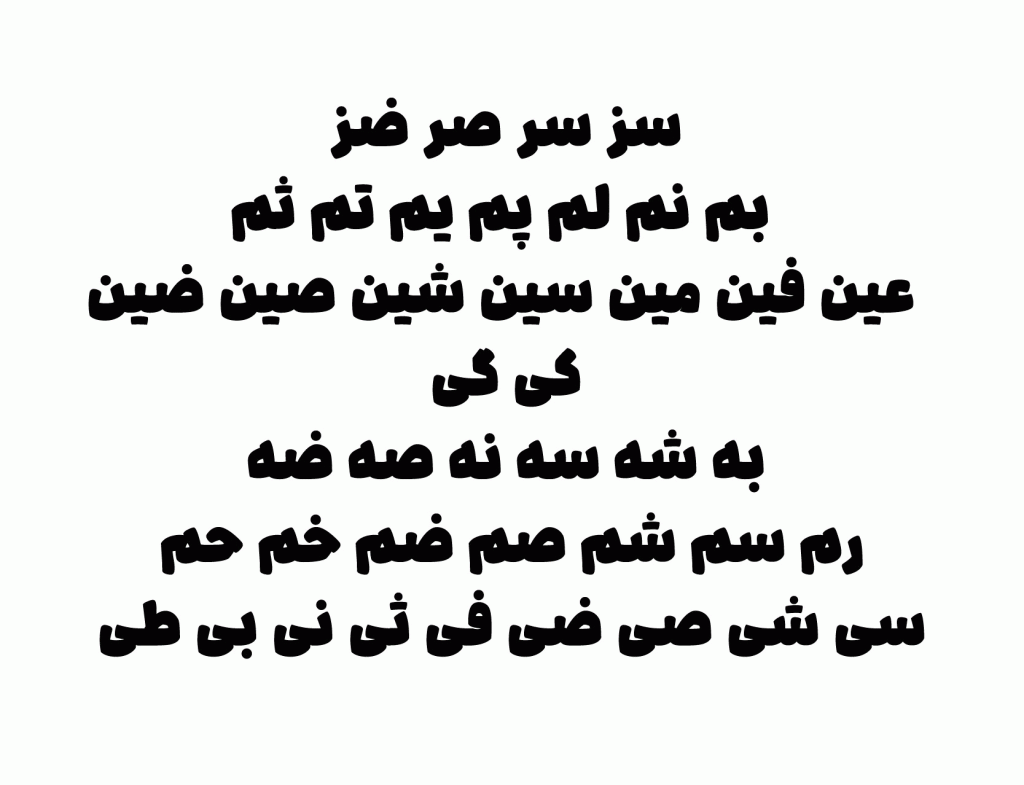
فونت چکاد – قلمی برای جذب نگاه مخاطبان
فونت چکاد تایپ فیسی که ایده و مدل طراحی آن از به قرن ها پیش باز می گردد . ای قلم با اقتباس از خط سکه نقره شاه اسماعیل اول محفوظ در کتابخانه ملک طراحی گردیده است. ویژگی اصلی چکاد نمایشی و جذابیت آن می باشد. و برای عناوین و عبارت های کوتاه بسیار مناسب است. برای تیتر های تبلیغاتی و مطبوعاتی در جذب مخاطبان نقش عمده ای را ایفا می کند.
دومین ویژگی چکاد لحن صمیمانه و غیر رسمی آن است چرا که با دقت در فرم های آن می توان دریافت که منحنی های نرم با زوایای داخلی و خارجی به دور از تندی و تیزی های بیش از حد حس صمیمی و دوستانه ای را به خواننده منتقل می کند و تلفیق همزمان حرکات مدور و هندسی، لحنی پویا و صمیمی را تداعی می نماید. ضمنا در این قلم حفظ قواعد تناسبات اندازه خوشنویسی رعایت گردیده است تا حد ممکن حروف به صورت جمع و جور و با فضای منفی فشرده طراحی گردد از جنبه هایی می توان چکاد را تا حدی نزدیک به قواعد خط نسخ به شمار آورد.
چکاد و پشتیبانی از حروف جایگزین
فونت چکاد همچنین از حروف ها و لیگیچر و کارکترهای جایگزین پشتیبانی میکند وجود این ویژگی در هر تایپ فیسی علاوه بر افزایش میزن جذابیت و زیبایی سبب خلق تنوع و دوری از یکنواختی در طراحی می گردد. در فایل راهنمای این تایپ فیس نحوه فعالسازی لیگیچرها آموزش داده شده است.
از جمله این حروف جایگزین در چکاد می توان به کارکتر هایی مانند ” ر – ز – ی – ک – گ – م – ه … ” اشاره نمود . شما دوستان عزیز می توانید تصاویر نمونه از این فونت زیبا را مشاهده و یا در آزمایشگاه سایت ما این فونت را با عبارت های خود آزمایش کنید.